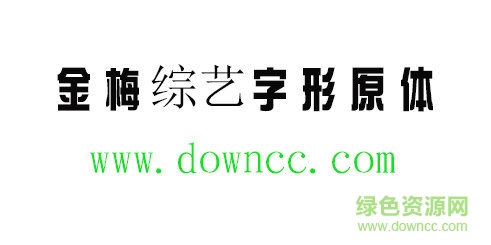
金梅綜藝字形原體字體
金梅綜藝字形原體是一款非常好看的金梅字體,英文、阿拉伯數(shù)字、中文皆支持,在字體上進行了加粗,起到了非常醒目的效果,而且字體深受廣大用戶的喜愛和好評,應用范圍也非常的廣泛,你可別錯過了,歡迎有需要的朋友到綠色資源網(wǎng)下載使用!
該字體大方得體,字形進行了加粗加長處理,整體效果十分出色,可以用于包裝印刷、簽名設計、電影字幕、圖形設計等領域。